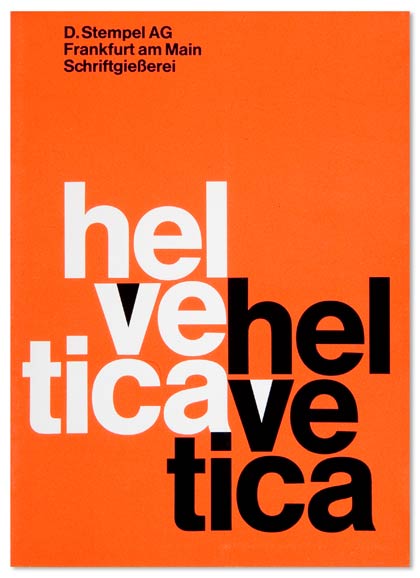
مکس میدینگر طراح سبک سوئیسی
مکس میدینگر ۲۴ دسامبر ۱۹۱۰ در زوریخ سوئیس  متولد شد. در ابتدا پدرش اصرار داشت که حرفه ای در زمینه حروفچینی را شروع کند، او در دفتر چاپ که توسط ژاک بولمن اداره می شد، شاگردی کرد. سپس بین سال‌های 1926 و 1930به عنوان یک تایپوگراف در مدرسه هنریKunstgewerbeschule در زوریخ آموزش دید. در 26 سالگی به عنوان تایپوگراف در بخش تبلیغات گلوبوس، یک فروشگاه زنجیره ای مشهور، مشغول به کار شد. پس از 10 سال تصمیم گرفت مشاور مشتری و نماینده فروش حروف چاپی شود. میدینگر  اولین تایپ فیس خود را در سال 1954ایجاد کرد، یک سریف متراکم به نام Pro Arte. سپس راه برادرانش را ادامه داد و به عنوان گرافیست آزاد و مشاورتبلیغاتی مشغول به کار شد.
مکس میدینگر
در نهایت ادوارد هافمن، میدینگر را به طراحی تایپفیس جدید sans serif ترغیب کرد تا از آن برای نمایندگی شرکت خود 'Haas type foundry' استفاده کند. این ایده‌ای بود که  نوع معروف Neue Haas- Grotesk را تولید کرد. همانطور که توسعه تایپ فیس او به هلوتیکا تبدیل شد، او به حرفه آزاد خود ادامه داد و مجبور شد مدت زیادی صبر کند تا به رسمیت شناخته شود که شایسته آن نیز بود. مکس میدینگر به همراه ادوارد هافمن، یکی از تأثیرگذارترین تایپ‌فیس‌ها را در تاریخ تایپوگرافی خلق کردند. Neue Hass-Grotesk که در جهان به نام هلوتیکا شناخته می شود. Helvetica که برای دنیای صنعت طراحی شده بود، جهان را در بر گرفت و توسط شرکت ها، هنرمندان و طراحان به طور یکسان مورد استقبال قرار گرفت. نزدیک به 50 سال است که Helvetica بر دنیای تایپوگرافی تسلط داشته است و امروزه همچنان استاندارد در خوانایی، سادگی و فراگیری را حفظ کرده است و با ظهور اینترنت و نرم افزار وب، هدف بزرگی را دنبال می کند.
تأثیر مکس بر جهان با Helvetica برای هر نوع دیگری بسیار مهم است، این نوع فونت در کنار Times New Roman بیشترین استفاده را دارد و به راحتی خوانده می شود. در دنیای طراحی گرافیک، تایپ فیس Helvetica او به دلیل محبوبیت و استفاده بیش از حد از آن در صنعت، اجتناب می شود. با این حال، او هنوز هم بر بسیاری از طراحان مانند جوزف چرچوارد که در سال 1972 تایپ فیس Churchward Maricia را بر اساس حروف Pro Arte که قبلا توسط میدینگر ایجاد شده بود، طراحی کرد تحت تأثیر قرار می دهد. همچنین به نام Helvetica که بر طیف گسترده‌ای از فونت‌ها در سراسر جهان تأثیر گذاشته است، مانند Arial طراحی شده توسط پاتریشیا ساندرز و رابین نیکلاس در سال 1982 و Alte Haas Grotesk یک نسخه مدرن طراحی شده توسط Yann Le Coroller در سال 2007، تأثیر گذاشت.
مکس میدینگر در  8 مارچ 1980 چشم از جهان فرو بست.